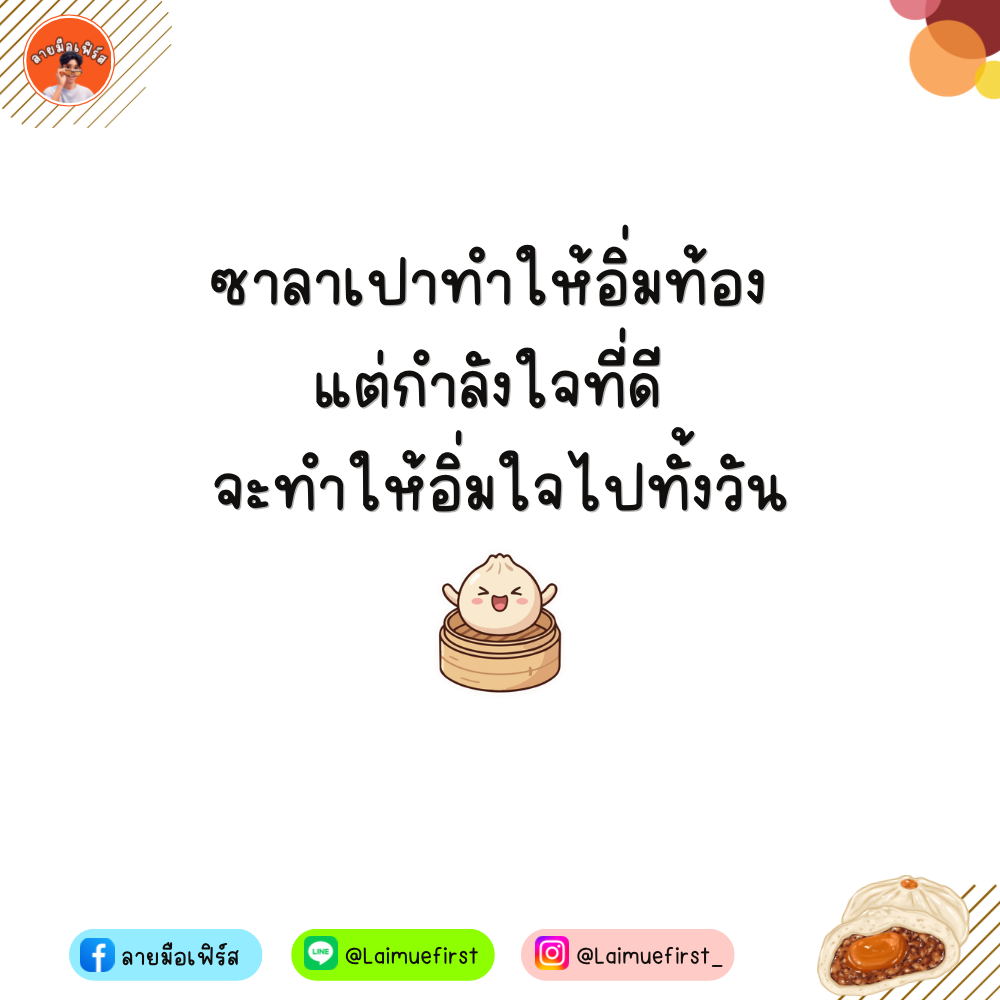
ฟอนต์ลายมือ ซาลาเปา (LMF Salapao)
ฟอนต์ลายมือสไตล์น่ารักปุ๊กปิ๊ก อ่านง่าย รองรับ Microsoft, Photoshop, Illustrator, CapCut, ibisPaint, Procreate, Good Note และแอปฯ ต่างๆ ที่มีให้ติดตั้งฟอนต์